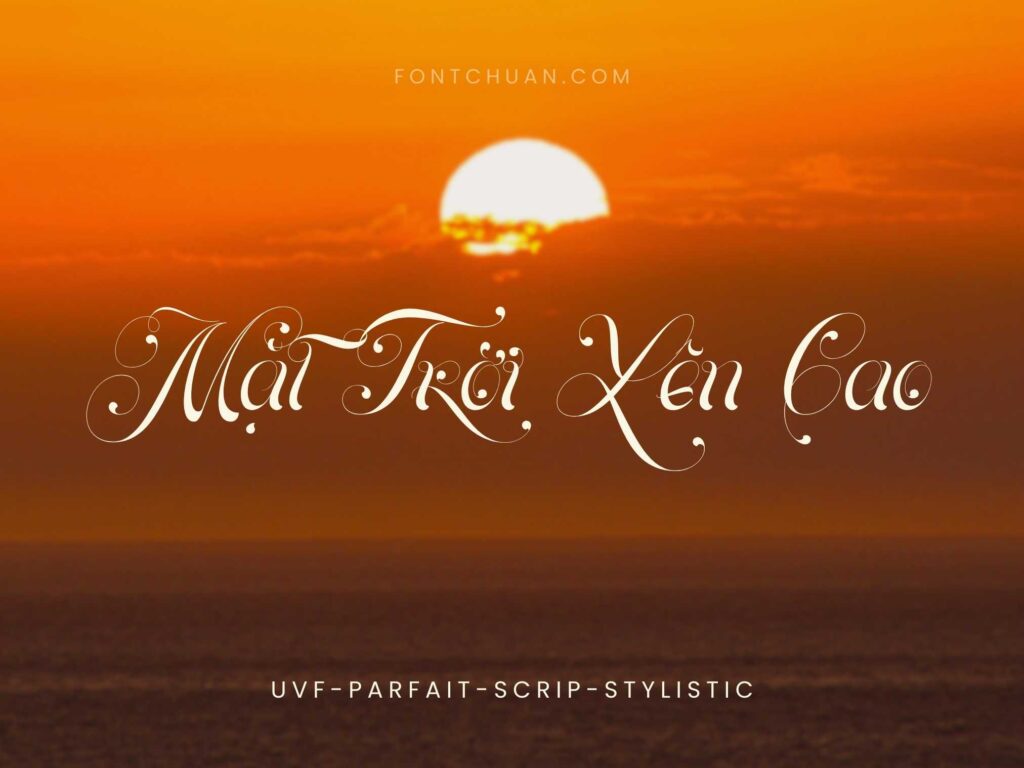
Font UVF Parfait Scrip Stylistic Việt Hóa
Parfait Script là một font chữ script lấy cảm hứng từ chữ viết Spencerian và nghệ thuật viết cọ nhọn, được thiết kế bởi Maximiliano R. Sproviero trong khoảng thời gian từ năm 2009 đến 2010. Font này nổi bật với hơn 850 ký tự, bao gồm nhiều chữ thay thế và ligature, giúp người dùng linh hoạt trong việc tạo ra các thiết kế độc đáo và sáng tạo. Với các đường nét mềm mại và uyển chuyển, Parfait Script mang lại cảm giác thanh lịch và tinh tế cho các dự án thiết kế.
Font này phù hợp cho các ứng dụng như thiệp mời, tiêu đề sách, thiết kế logo và các ấn phẩm nghệ thuật. Trong lĩnh vực sự kiện, Parfait Script có thể được sử dụng trong các dịp như lễ hội, lễ cưới và các sự kiện văn hóa. Ngoài ra, font này cũng thích hợp cho các ngành nghề như thiết kế đồ họa, nghệ thuật trang trí và xuất bản.
Bên cạnh các ứng dụng thanh lịch và tinh tế, Parfait Script còn là một font valentine lý tưởng để thiết kế các sản phẩm lãng mạn và ngọt ngào, như thiệp Valentine, banner hay poster dịp lễ tình nhân. Với các đường nét mềm mại, uyển chuyển và tinh tế, font này giúp các thiết kế vừa sang trọng, vừa mang cảm giác ấm áp, gần gũi, phù hợp cho các dự án sáng tạo mang chủ đề tình yêu và các dịp đặc biệt.